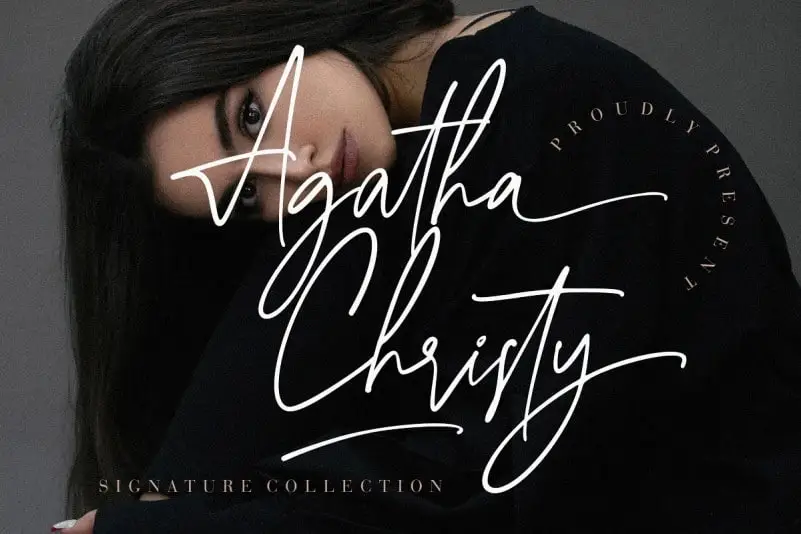
Agatha Christy Script Font – Download Grátis
A Agatha Christy Script Font é uma opção perfeita para projetos que precisam de um toque autêntico e delicado de escrita manuscrita. Criada pelo Creatype Studio, esta tipografia casual e limpa foi projetada para dar vida a ideias e experiências em várias áreas do design gráfico. Suas alternativas para letras minúsculas, aspas e ligaturas permitem que o designer realize trabalhos criativos sem se preocupar com erros de digitação ou problemas de estética. A Agatha Christy é perfeita para criar identidades visuais, logos, designs de casamentos, postagens nas redes sociais, anúncios, embalagens e embalagens de produtos, etiquetas, fotografia, marcas de água, convites e material gráfico personalizado. Ela se adapta às necessidades dos projetos, dando uma nota delicada e pessoal que torna a experiência do usuário única e memorável. Esta fonte é um recurso valioso para designers, especialmente aqueles buscando incorporar elementos manuscritos em seus trabalhos.